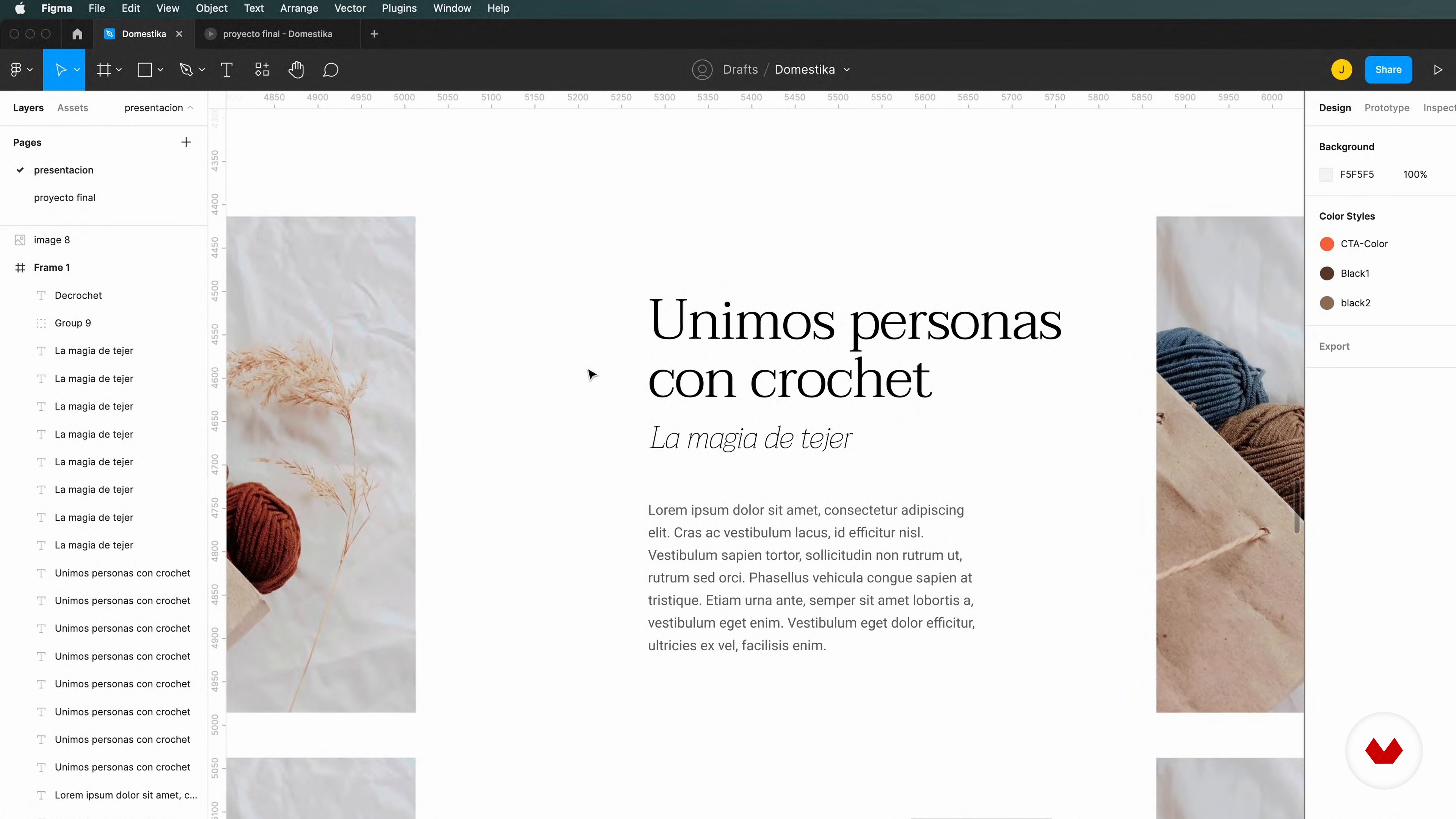
La tipografía adecuada
Sobre la videolección: La tipografía adecuada
Resumen
“Finalmente, te voy a hablar de la importancia de la tipografía y te explicaré cómo seleccionarla de forma adecuada para que se ajuste lo mejor posible al proyecto que tengas entre manos.”
En esta videolección, Juan Mora aborda el tema: La tipografía adecuada, que forma parte del curso online de Domestika: Diseño UX UI para landing pages: cuenta una historia única. Aprende a crear una landing page con Figma, conectando con los usuarios a través del storytelling .
Transcripción parcial del vídeo
“ La tipografía adecuada En esta lección vamos a aprender cómo elegir la tipografía adecuada. Es un paso muy importante para cualquier diseño, ya que la tipografía, aparte de contar un mensaje, también representa el estilo de una marca. Normalmente yo voy a Google Fonts. Es mi sitio web favorito para encontrar diferentes tipos de fuentes. Muchas personas empiezan a buscar directamente hacia la fuente que más les guste, pero la fuente cambia según las palabras que estén escribiendo. Entonces, ya para hacer una búsqueda más acertada, les recomiendo colocar ciertas palabras relacionadas con la...”